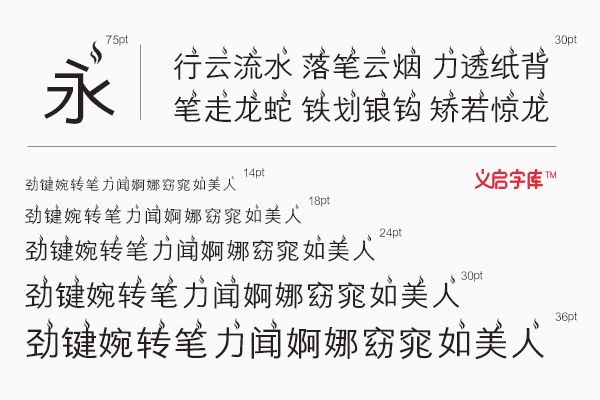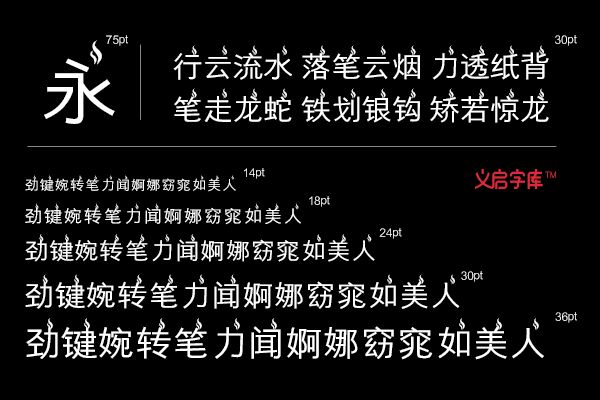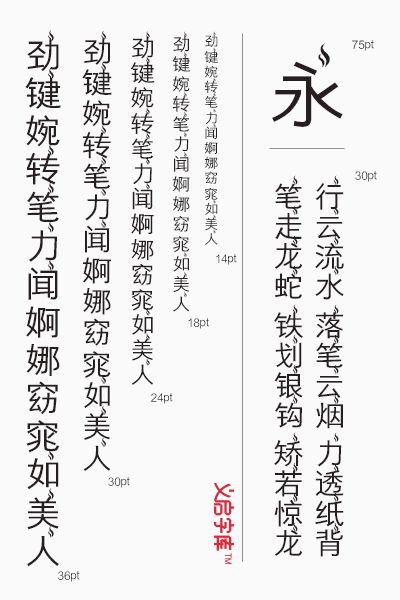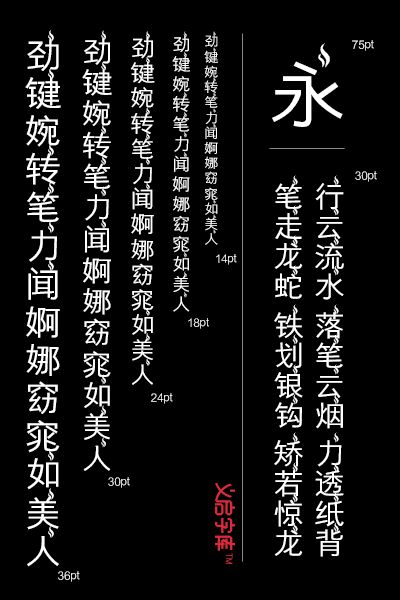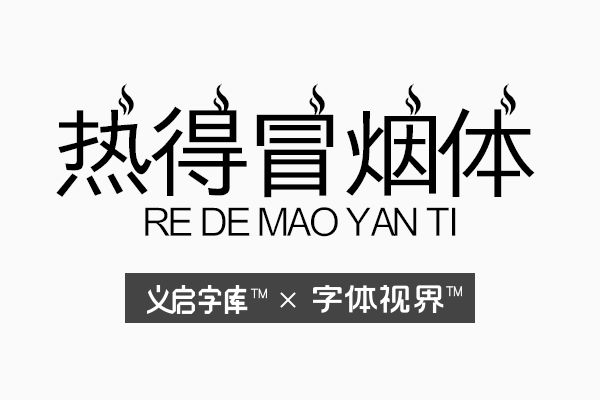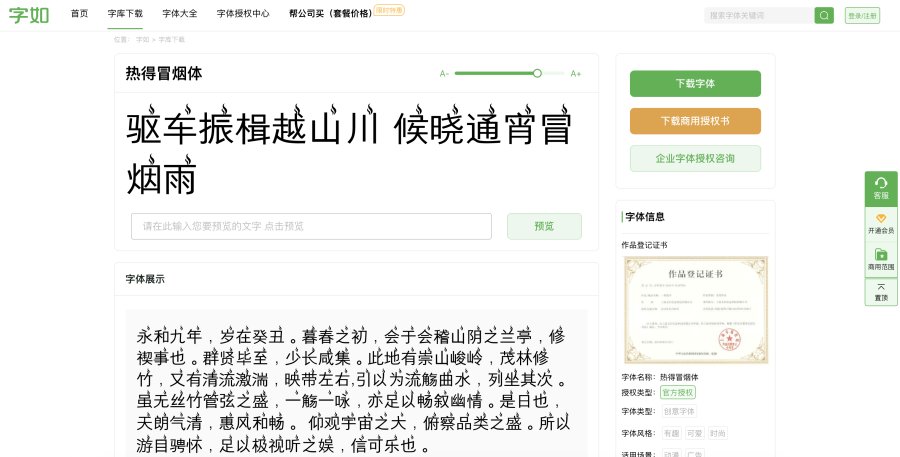
自打入夏以来,就独得太阳恩宠,我告诉太阳一定要雨露均沾,可是太阳非不听呢~就晒我,就晒我,把我热得都冒烟了~
在炎热的夏天里,你有哪一天不是被热得像洗了个热水澡似的,又有哪一天不是被热得冒烟?而今天我们的这款热得冒烟体字体就是受了夏天的启发,它在每个字的右上角方都会加两条一长一短的烟,看起来就好像这个字就是人,在这个炎热的夏天里,我们的后脑勺热得冒烟了,这种字体给人的感觉仿佛就是夏天正无时无刻的伴随着我们,给我们有开心又有烦恼。
义启热得冒烟体字体是一款由义启字库开发的一款中文艺术字体,这款字体的笔触较为纤细,字体清晰,字形潇洒,在每个字体的上方都会有一个火状的标示,表示很热很热。[热得冒烟体],在炎热的夏季人们总会说“都热得冒烟了”,但是会冒烟的可不止人,还有字体,不信你就来看看,字体都热得冒烟了,可能设计师夏天被热惨了,所以才创造了这个热得冒烟字体,每一个字都活冒出一缕青烟,真的是冒烟了,非常好玩。
热得冒烟体字体主要特性:
1、加粗宋体,类似于黑体,比较方正;
2、每一个字都会冒出热,体现了在炎热的夏季,热得冒烟了。
在这炎热的夏天里,你会喜欢这夏天的太阳的恩宠?喜欢这款“自私”的热得冒烟体字体?